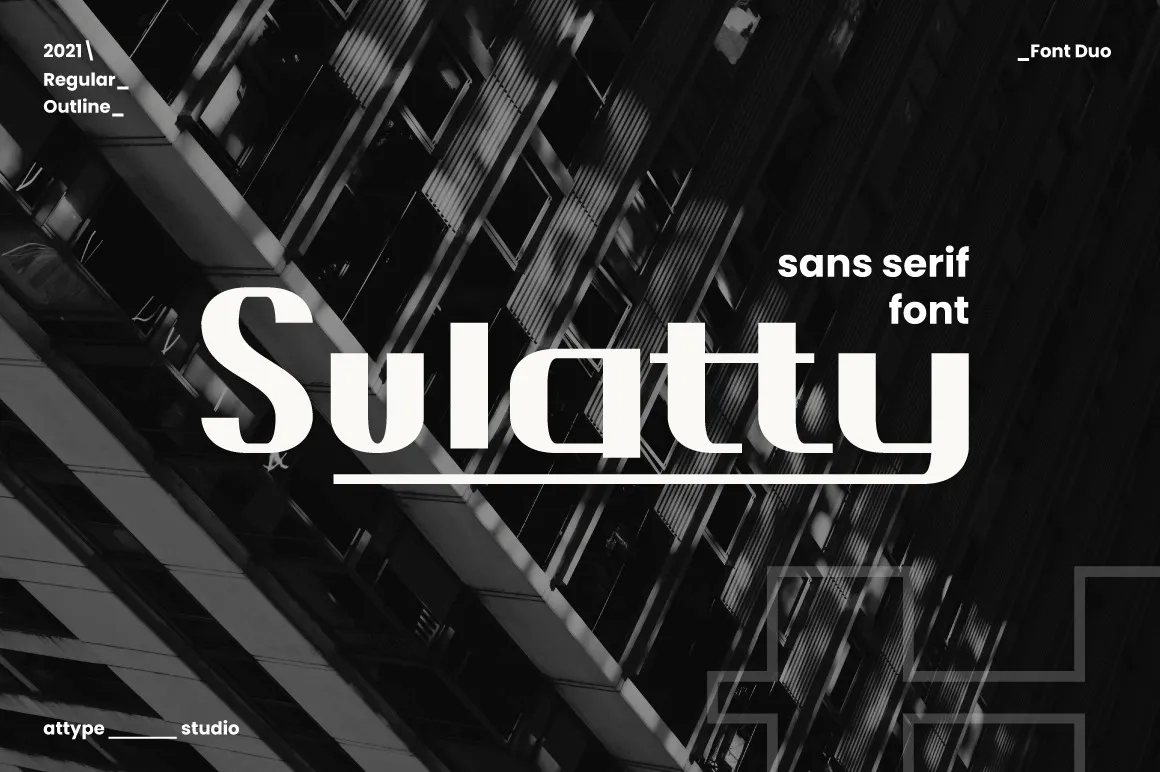
Sulatty Font – Fonte Grátis
Sulatty Font
Sulatty é uma fonte sans-serif que oferece uma nova perspectiva para a tipografia moderna. Seu conceito inovador está a cargo do attypestudio, um designer de renome na comunidade gráfica. Este tipo de letra apresenta duas variações estilísticas e terminações alternativas para os caracteres ‘j’, ‘g’ e ‘y’. Essas opções adicionais permitem criar uma tipografia encantadora que traz vida a qualquer projeto design, seja ele um logotipo, um livro de arte ou até mesmo um site. Sulatty é um exemplo de como uma única fonte pode se tornar uma ferramenta versátil e criativa para artistas digitais.